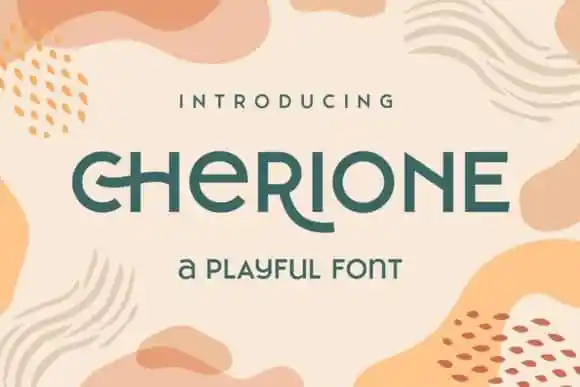
Cherione Sans Serif Font – Download Grátis
A ‘Cherione Sans Serif Font’ é uma família moderna de serif semicurva com linhas limpas e um amplo leque de ligaturas e alternativas. Suas linhas finas e achatadas dão à fonte um olhar elegante e minimalista, combinado com sua versatilidade em combinações criativas de tipografia para criar uma aparência chic e única. Além disso, o equilíbrio geométrico dos caracteres foi cuidadosamente ajustado para parecer elegante e minimalista. Esta fonte oferece um visual inovador, com letras minúsculas que têm a mesma altura que as maiúsculas, resultando num look descontraído e divertido, combinado com uma aparição sofisticada e moderna. Se você está procurando por uma fonte versátil para projetos digitais ou impressão, esta é definitivamente uma opção interessante a considerar.